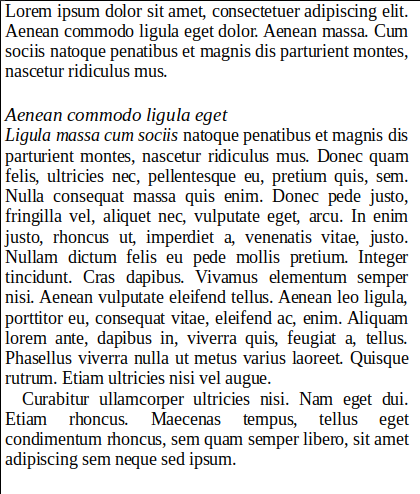
Kursivschrift nach kursiver Überschrift?
derzeit betreue ich eine wissenschaftliche Publikation, die in einem vorgegebenen Corporate Design erschienen soll. Dieses sieht Überschriften in 4 Hierarchieebenen vor (Ü1–Ü4). Nun folgt an einer Stelle im Manuskript auf eine Ü4 (laut CD: gleiche Schriftart wie Mengentext, allerdings 1 Pkt größer und kursiv) Mengentext, der mit einer Hervorhebung beginnt. Hierfür sieht das CD als einzige Möglichkeit Kursivierung vor (Schriftart des Mengentextes, kursiv). Auf diese Weise steht also unter der kursiven Überschrift erst einmal kursiver Text, bevor es recte weitergeht. Bei Durchsicht des Satzes hatte ich ein Störgefühl beim „Aufeinanderprallen“ dieser beiden Kursivierungen.
Meine Frage: Ist das typografisch so korrekt oder müsste hierfür (evtl. redaktionell) eine andere Lösung gefunden? Gibt es hierzu eine typografische Regel?
Ich habe den Fall mal in einer ähnlichen Schriftart mit Blindtext nachgestellt (s. Screenshot). (Die Wortdopplung in Überschrift und kursiv hervorgehobenem Mengentext entspricht einer Dopplung im Original.)
Noch zum Hintergrund: Da ich den Text nicht verfasst habe (sondern lediglich den Publikationsprozess koordiniere), kann ich den Text nicht nach Belieben ändern.
Mich würde das sehr nerven. Gibt Dir das CD auch Einzüge vor? Wenn nicht, schau mal, ob es noch doof aussieht, wenn Du Bei jedem neuen Absatz mit einer kleinen Einrückung beginnst, auch wenn der Usus abnimmt, Absätze nach einer Überschrift einzurücken. Oder etwas mehr Luft zwischen Überschrift und Textkörper? Eine deutlichere optische Trennung würde ich bevorzugen.
Gibt Dir das CD auch Einzüge vor?
Ja, leider. Die erste Zeile eines Absatzes muss eingerückt werden – außer beim ersten Absatz nach einer Überschrift, dort darf die erste Zeile nicht eingerückt werden.
Oder etwas mehr Luft zwischen Überschrift und Textkörper?
Auch das ist (leider) im CD geregelt: Bei der Ü4 (und der Ü3) soll keine Leerzeile zwischen Überschrift und dem darunter folgenden Text stehen (anders als bei Ü1 und  Ü2). (Und Abstände, die kleiner als Zeile sind, würden – abgesehen davon, dass sie laut CD nicht erlaubt sind – wohl auch Unruhe in den Satz bringen.)
Eine deutlichere optische Trennung würde ich bevorzugen.
Mich würde das nicht so sehr stören, solange die Überschriftszeilen deutlich kürzer sind als die Textzeilen. Dagegen finde ich den Größenunterschied von nur einem Punkt von der Überschrift zum Fließtext völlig daneben. Unterschiede müssen deutlich sein, sonst empfindet man sie eher als Fehler.
Da wird man nicht viel machen können, wenn die Vorgabe so unsinnig mit einem Punkt Unterschied ist. Das sehe ich wie Dieter :nicken:
Darf lt. CD die Überschrift gesperrt werden? Das könnte zur Unterscheidung beitragen. Sonst würde ich pragmatisch rangehen: Machen, was erlaubt ist, auch wenn es nicht gut aussieht. Eine wissenschaftliche Publikation ist ja meist umfangreich, da findet man sich auch trotz solcher Stolpersteine zurecht.
ich denke die unterscheidung ist klar und verwechslung schon wg. der leicht unterschiedlichen schriftgröße ausgeschlossen. aber wir sind uns einig: schön ist was anderes. (imho lieget der fehler in der definition, dass die zwitis auf unterster ebene kursiv sein müssen. würde ich im leben nicht machen)
Dass ein Text auf Registerhaltigkeit (Leerzeilen) aufgebaut ist, ist typografisch richtig und für den Lesefluss wichtig.
Um aber eine bessere Unterscheidung von Titel und kursivem Fließtext zu erreichen, könnte man die Leerzeile oberhalb des Titels um ca. ⅓ verringern und den Anteil der Verringerung unter den Titel einfügen. So würde der Fließtext registerhaltig bleiben und übersichtlicher werden.